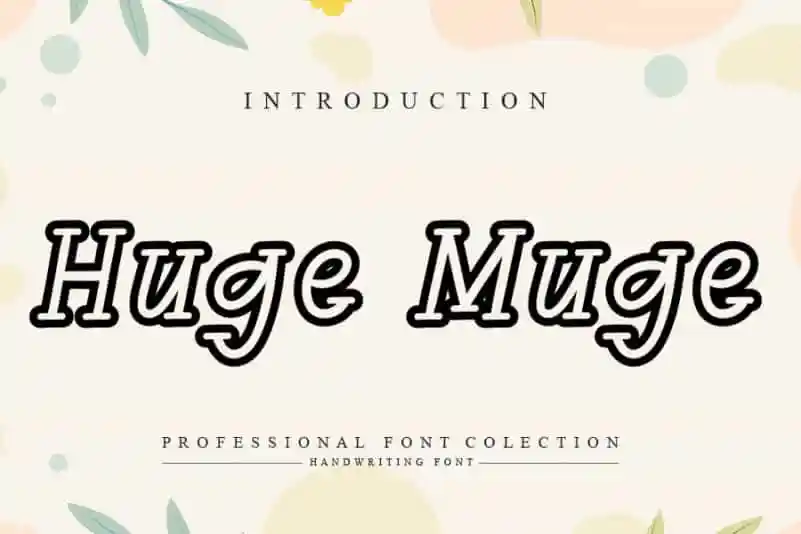
Huge Muge Handwritten Font – Download Grátis
Huge Muge Handwritten Font é uma fonte escrita a mão moderna com um aspecto único que traz um toque autêntico à sua próxima criação de design. Suas curvas elegantes e linhas levementes garantem um estilo distintivo capaz de se destacar em qualquer projeto, seja para criar identidades de marca memoráveis, entregar mensagens impactantes nas cabeçalhos, apresentar detalhes meticulosos nos designs para casamentos ou convites especiais, assinar textos de forma criativa, criar rótulos personalizados ou mesmo na elaboração de logotipos únicos. Esta fonte é a escolha perfeita para aqueles que buscam um toque autêntico e artesanal em seus projetos digitais, sem comprometer o padrão moderno e elegante. O designer andikastudio criou uma versão que valoriza os detalhes das escritas a mão, tornando-a perfeita para aquelas criações que necessitam de um toque pessoal e autêntico. Com Huge Muge Handwritten Font em seu arsenal de ferramentas de design, você pode trazer ainda mais vida à sua produção digital, garantindo que cada detalhe seja único e profissional ao mesmo tempo.